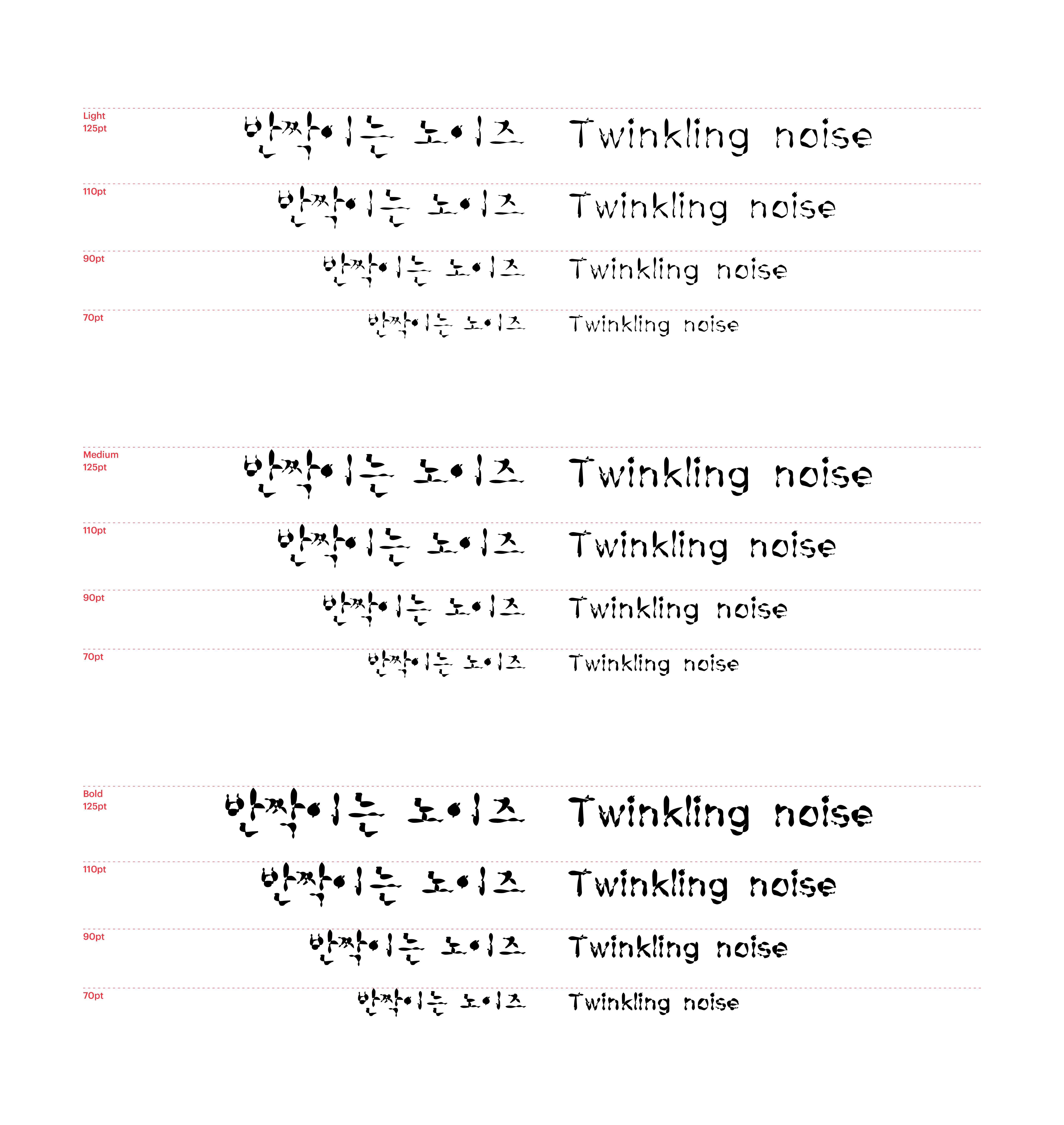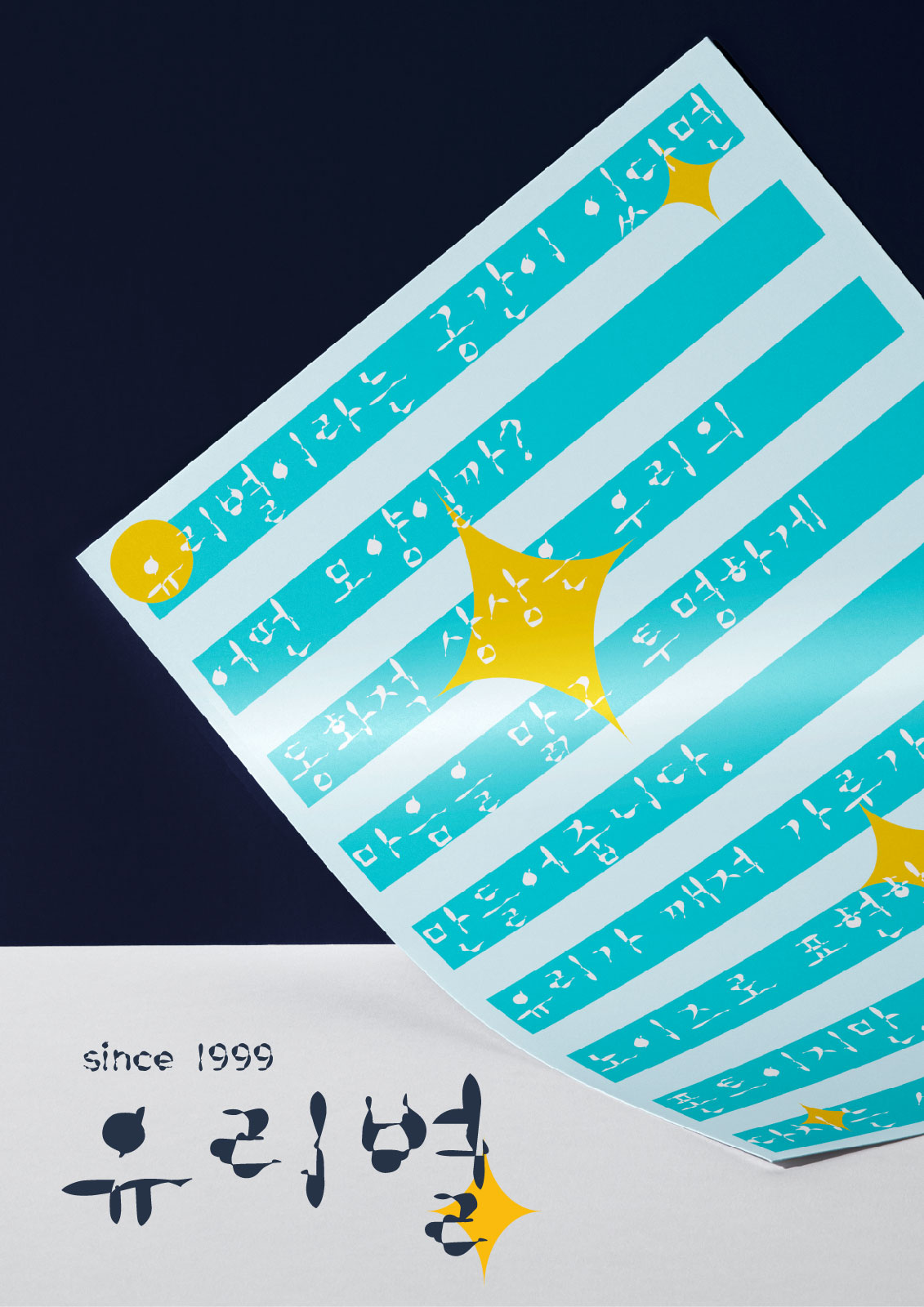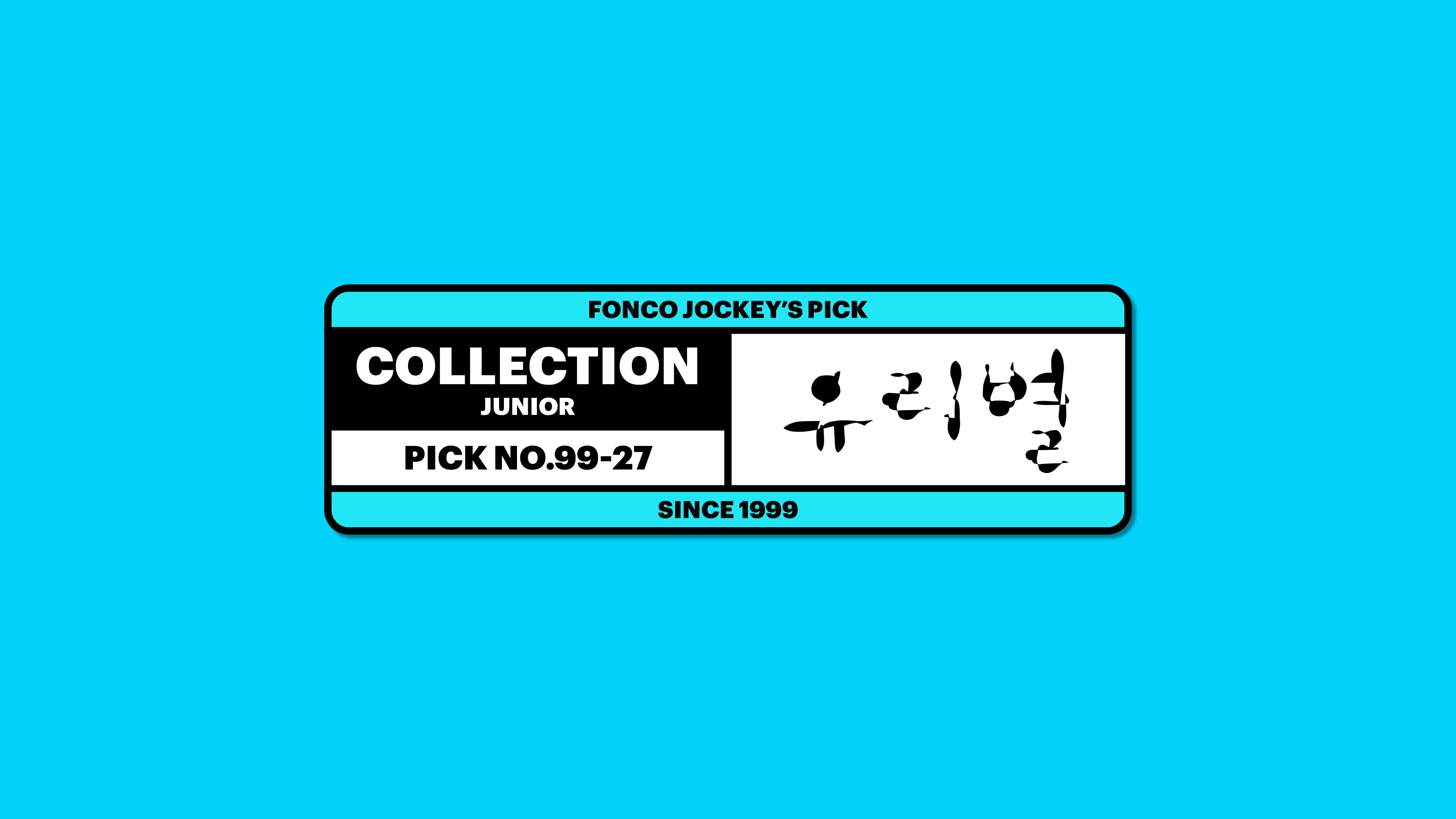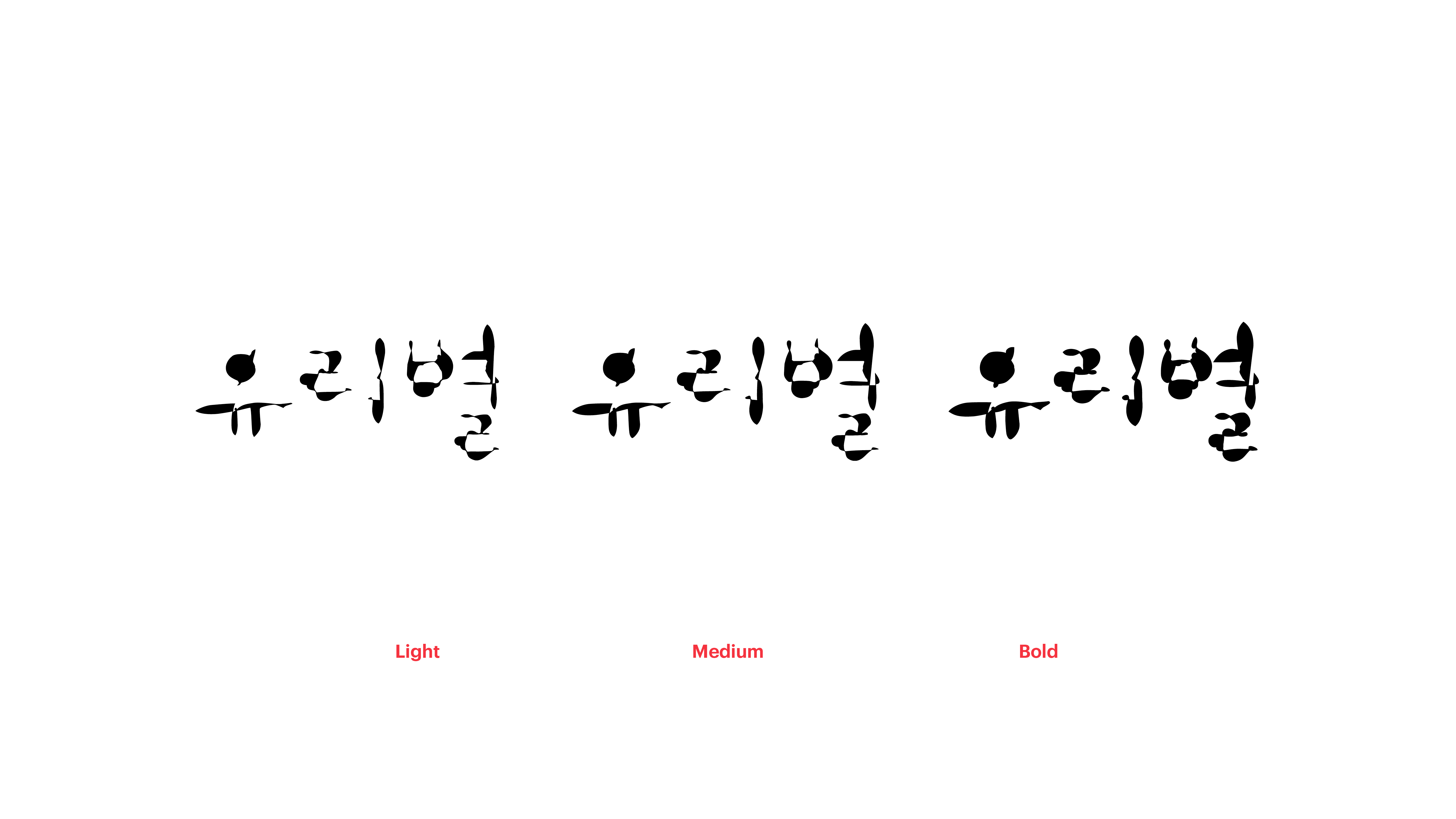
유리별
Yoon 유리별
동화적 상상은 우리의 마음을 맑고 투명하게 만들어줍니다. 이 독특한 폰트를 좀 보세요. “유리별이라는 공간이 있다면 어떤 모양일까?”하는 상상을 폰트로 구체화해보았답니다. 유리가 깨져 가루가 날리듯 노이즈로 표현한 폰트이지만, 아무도 다치는 사람은 없을 거예요. 빛을 받아 반짝이는 아름다운 공간만을 상상했거든요.